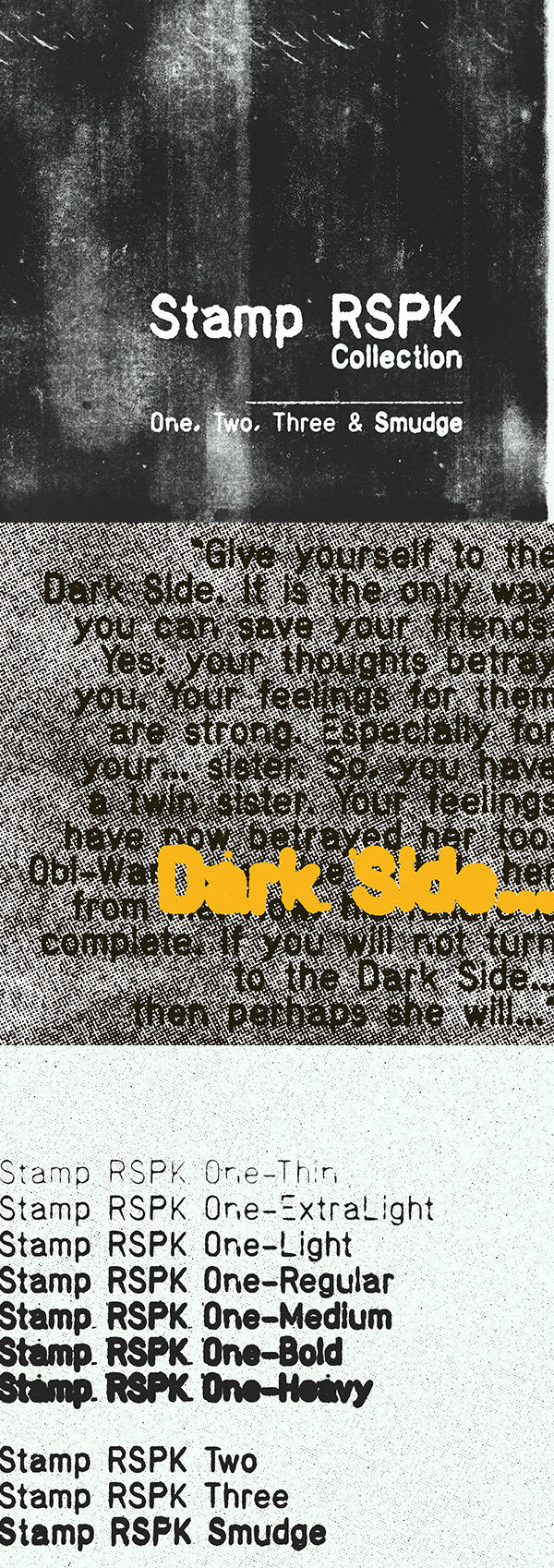
Дополнения Шрифты Татьяна Гапонова 22 августа 2017 Шрифт - Stamp Декоративный шрифт имитирующий машинопись. Формат - OTF. Размер - 1 мб. Скачать Шрифт - Stamp